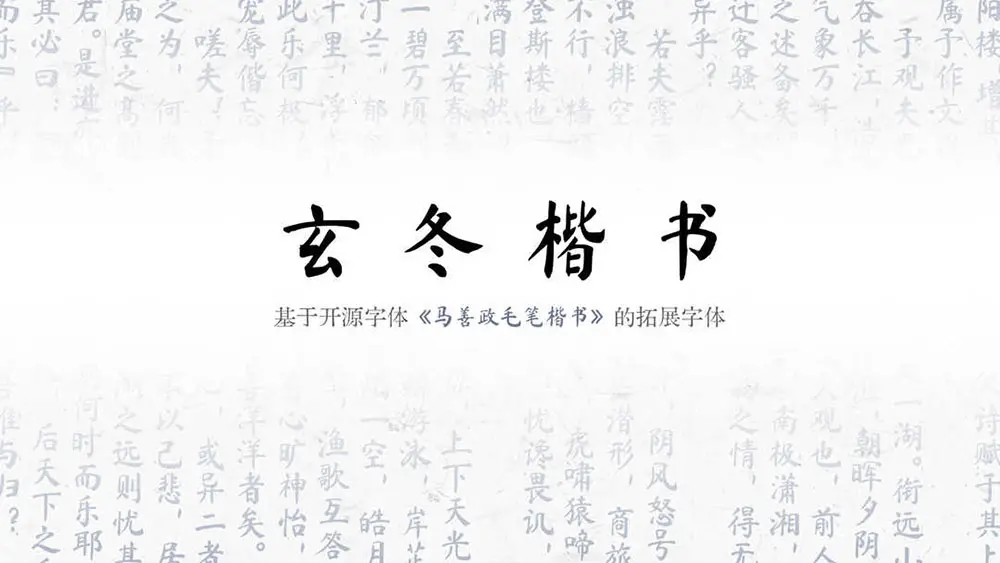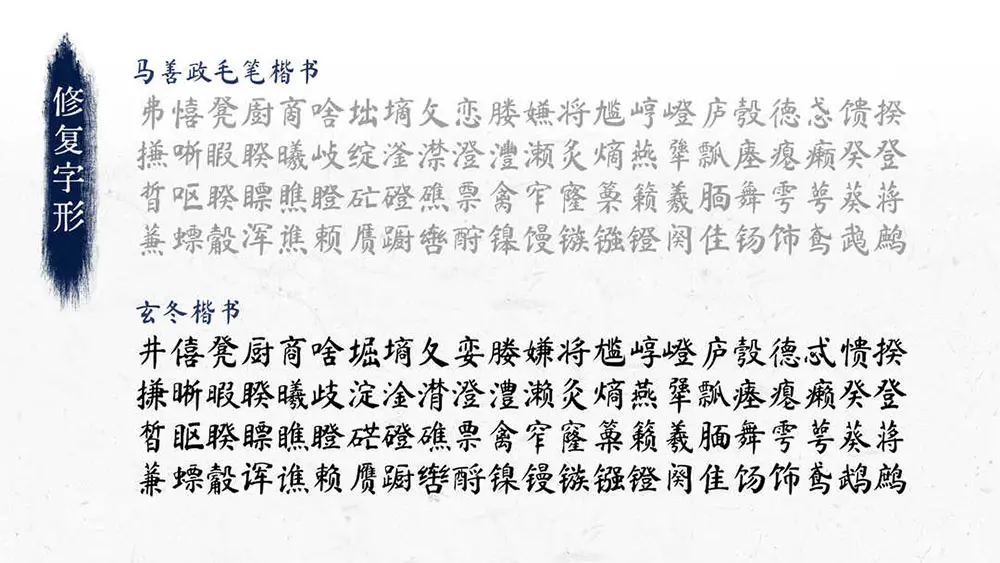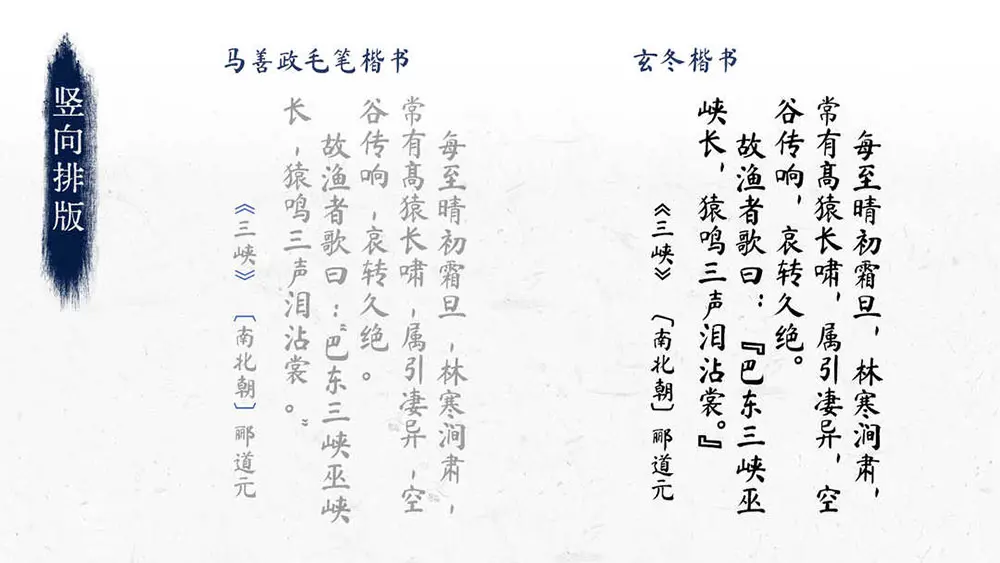
玄冬楷書是基於開源字體《馬善政毛筆楷書》的拓展字體。在原版的基礎之上修復了錯誤的字形並添加豎排排版的特性。
修復以下88字:井僖凳廚商啥堀墒夂孌媵嫌將尷崞嶝廬彀德忒憒揆搛晰暇睽曦歧澱淦潸澄澧瀨灸熵燕犟瓢瘞癟癩癸登
皙瞘睽瞟瞧瞪硭磴礁票禽窄窿篥籟羲靦舞雩萼葵蔣蒹螵觳諢譙賴贗躕轡酹鎳鏝鏃鏹鐙闋隹餳飾鳶鵡鷓。
調整都分漢字字面的問題。增加 vert 特性,用於豎向排版。新增“囉瞭”二字,補全一級通用規範字。